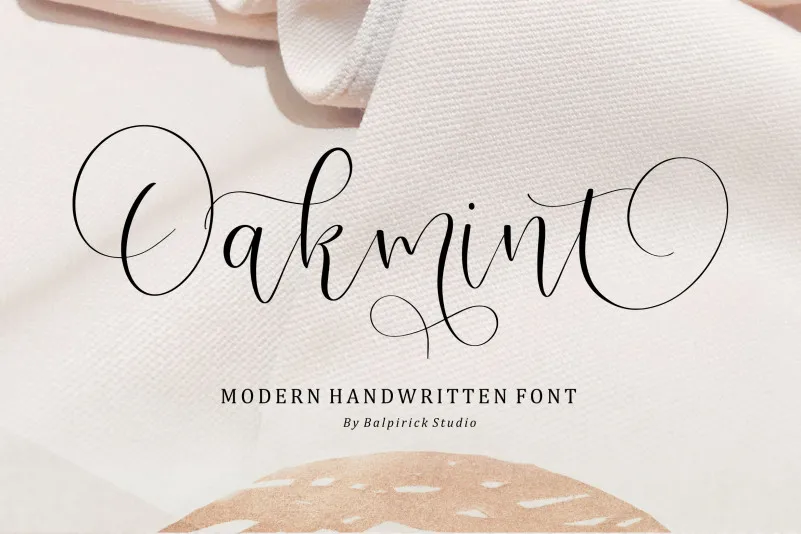
Oakmint Font – Download Grátis
A Oakmint Font é perfeita para projetos que exijam uma caligrafia elegante e versátil. Seja você criando embalagens de produto, desenvolvendo um projeto de marca ou montando um catálogo de revista, esta fonte oferece uma solução perfeita. A Oakmint também é adequada para as mídias sociais, onde seu impacto pode ser significativo e sua presença poderosa. Além disso, não importa o uso que você fará, a Oakmint está aqui para dar um toque especial às palavras destacadas acima do fundo ou mesmo em cartões de casamento. Este é um verdadeiro atalho para expressar suas ideias com estilo e sofisticação. Idealmente destinada para quem busca uma fonte que dê vida aos seus projetos digitais, a Oakmint não apenas enriquece sua escrita, mas também torna seu design visual mais atraente. Com um uso versátil e criativo, é ideal para qualquer projeto onde você deseja destacar letras com presença. A Oakmint se destaca na categoria de fontes script por oferecer uma variedade única que permite expressar mensagens de maneira única e distintiva. Seja em sua próxima campanha social, no design da sua marca ou até mesmo nos detalhes de um casamento, a Oakmint está disponível para ajudá-lo a destacar suas mensagens e projetos visuais de forma sofisticada e impecável.